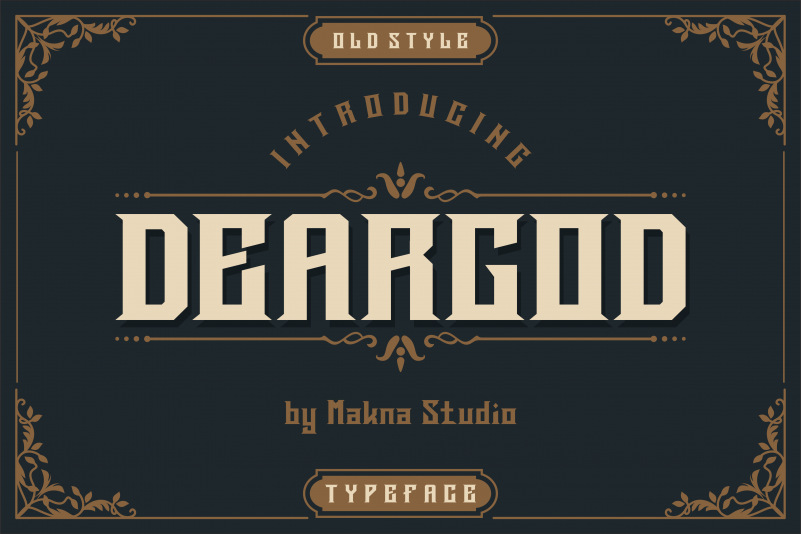
Deargod Font – Fonte Grátis
Deargod Font
A fonte ‘Deargod Font’ é uma criação única e poderosa, perfeita para ambientes que valorizam a personalidade e a presença visual forte. Ela é ideal para headlines, banners ou qualquer outro elemento de design que deseja destacar-se da multidão. Este tipo moderno com traços assertivos pode ajudá-lo a alcançar uma audiência mais ativa e interessada. Com um conceito leve mas persuasivo, essa fonte trará vida à sua marca e garantirá que seu design se destaque em qualquer contexto. Seja ele um site de negócios, um adesivo de carro ou até mesmo um cartaz no meio da rua, a ‘Deargod Font’ é uma escolha sólida para quem deseja comunicar com clareza e personalidade.